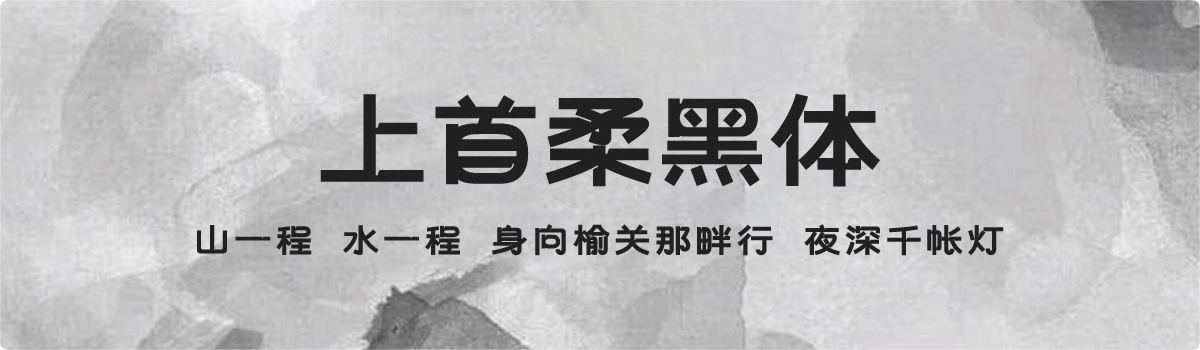
上首柔黑体
上首柔黑体,这款字体结构工整、笔画清晰,兼顾美观与易读性,适用于标题、正文、海报、包装、LOGO 等多种场景。字形优雅稳定,风格百搭耐看,适配日常排版与创意设计,让文字呈现更舒适、更具质感。上首柔黑体一笔一画,皆是细节,以均衡的比例、流畅的线条打造舒适视觉体验,字形端正大气,风格简约现代。无论是商业设计、品牌宣传还是日常排版,都能轻松驾驭,让文字更有格调与力量。上首柔黑体字体下载。